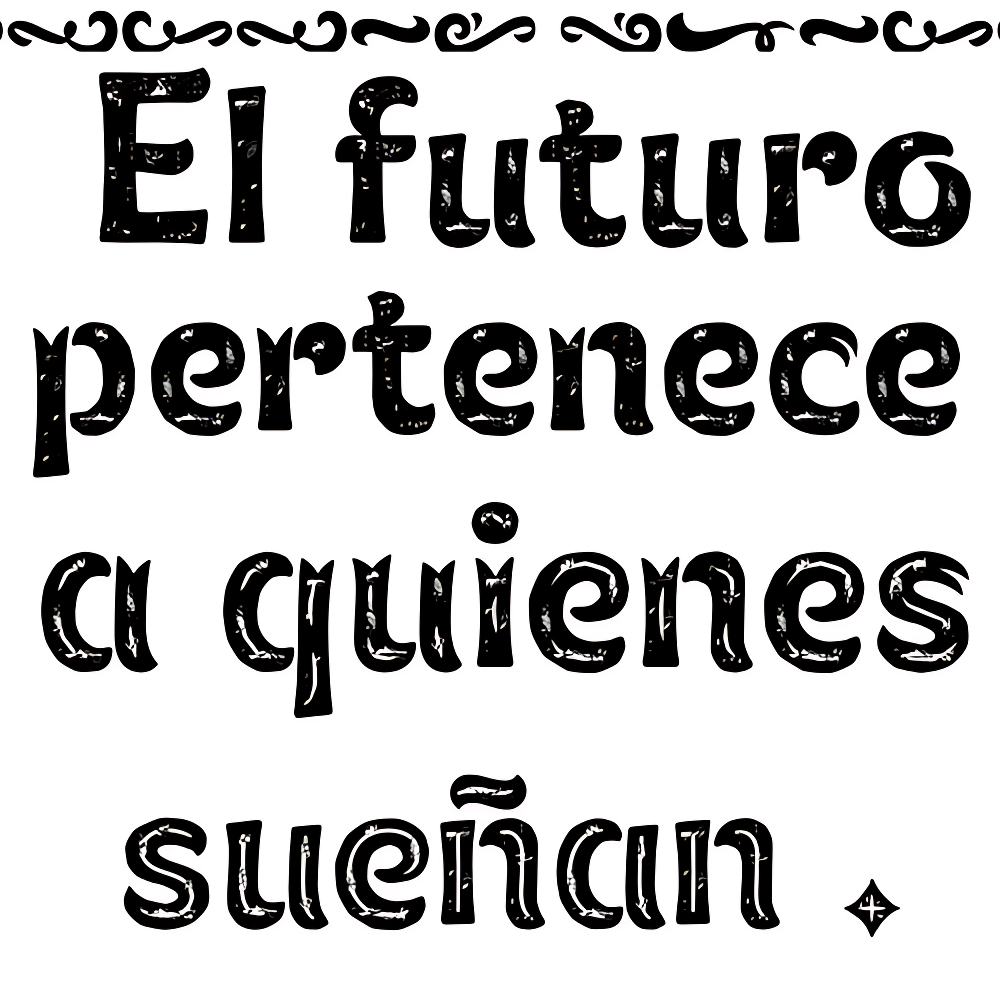
Elah Rock
| Descripción | "Elah Rock" es un nuevo tipo de letra diseñado especialmente para titulares centrados en el concepto "Rudo". Este tipo de letra transmite una sensación de crudeza y energía, perfecta para captar la atención del espectador y crear impacto visual. |
| Familia(s) | Elah Rock Regular, Elah Rock Tale Two, Elah Rock Tale, Elah Rock YOrnament, Elah Rock YOrnament Tale, Elah Rock XDingbats, Elah Rock XDingbatsTale, Elah Rock Inline |
| Estilos | 8 |